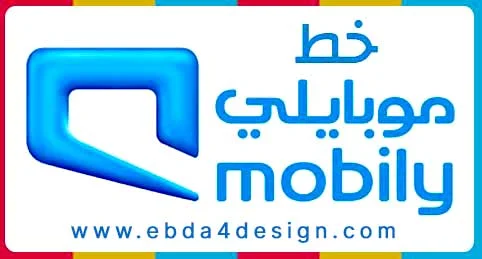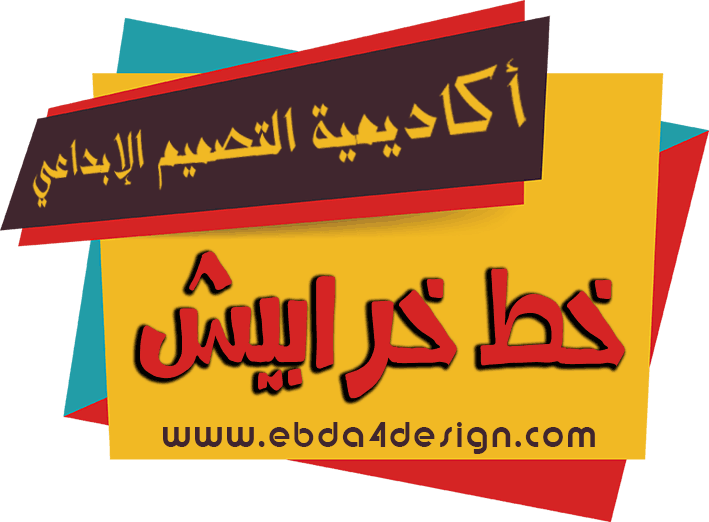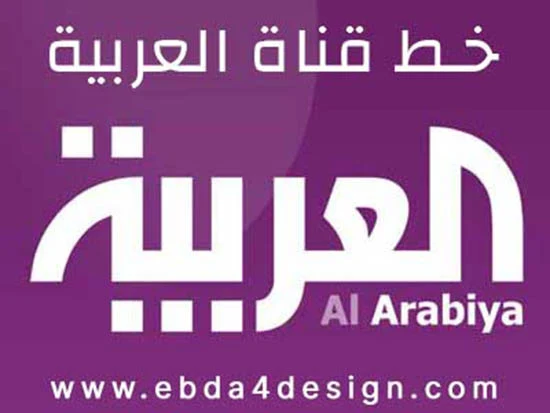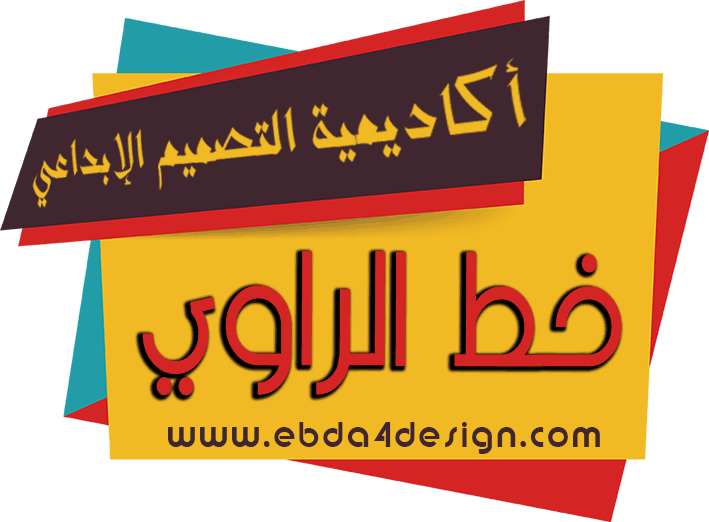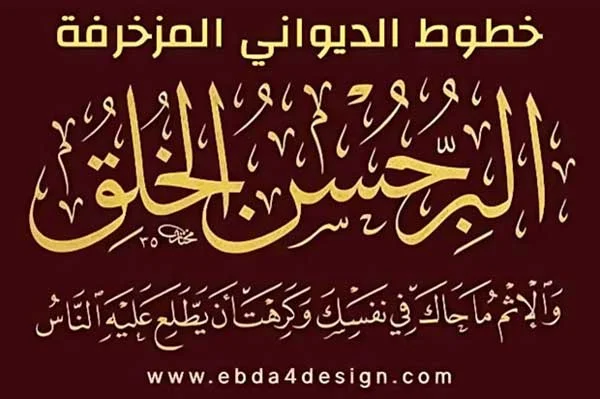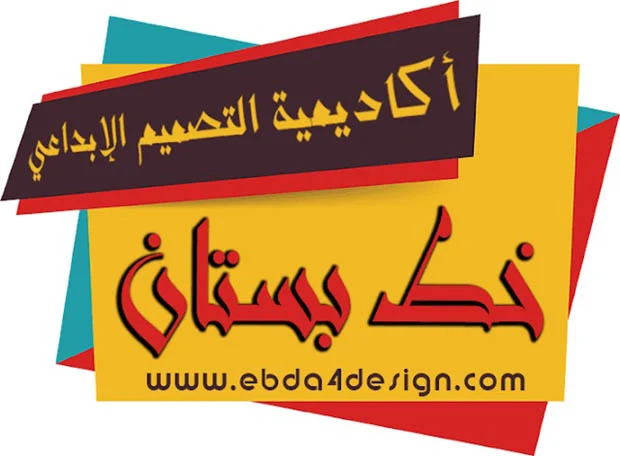
ستجد هنا أفضل مجموعة مختارة بعناية من خطوط التصميم العربيه."
اكتشف أفضل مجموعة خطوط عربية مزخرفة واحترافية للتصميم
والمنتقاه بعناية خصيصا لأغراض تصميم الجرافيك والإعلانات ومونتاج الفيديو
حزمة خطوط القرآن الكريم بجميع أنواعة
خطوط القرآن الكريم بجميع أنواعه بدقة عالية،
يدعم التشكيل الكامل وعلامات الضبط، مناسب للطباعة والنشر والتصاميم الإسلامية.
حزمة خطوط الديواني فارسي العادي والمزخرف مجانا بجودة عالية
حزمة خطوط الديواني والفارسية العادية والمزخرفة بتصميم أنيق يناسب العناوين والتصاميم الاحترافية،
حزمة خطوط النسخ العادية والمزخرفة مجانا بجودة عالية
حزمة خطوط النسخ العادية والمزخرفة مناسبة للكتابة والطباعة والتصاميم الإسلامية،
خط بوستان
خط الراوي
خط ميكس عرب
خط موبايلي
خط شروق
حزمة الخطوط الكوفية العادية والمزخرفة مجانا للتصميم بجودة عالية
الخطوط كوفية العادية والمزخرف مثالية للشعارات والعناوين والتصاميم الإسلامية،
خط تشانجا
خط خرابيش
خط الكليك
لتصميم وكتابة المخطوطات المزخرفة
خط جرافيتي
خط سلطان
خط عمر
خط قناة فنون الجديد
خط قناة دبي
خط قناة العربية
خط قناة الشارقة
خط قناة الاخبارية
خط طيور الجنة
خط ضحى ( الدوحة )
خطوط الرقعة
خط الحضاري
حزمة خطوط الحر
خطوط الأندلسي
حزمة خطوط الإعلانات والعناوين (الفونت)
خط أرامكو
خط المجاهد ( المحارب )